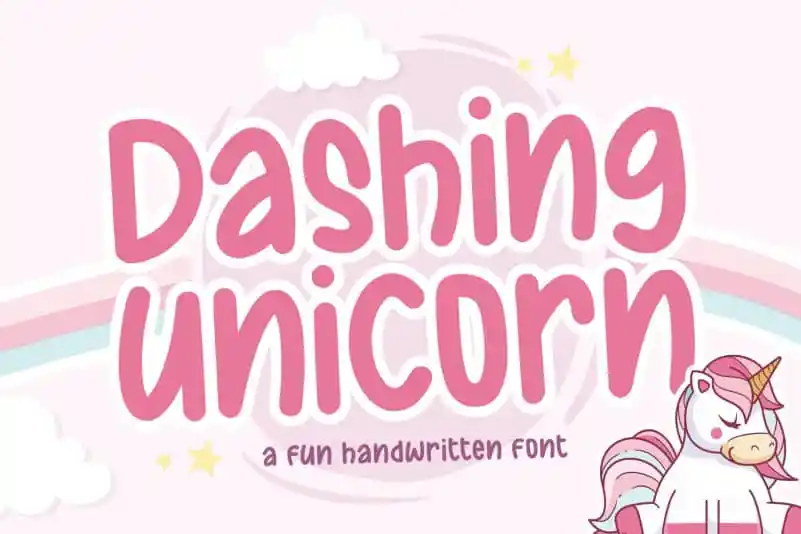
Dashing Unicorn Handwritten Font – Fonte Grátis
Dashing Unicorn Handwritten Font
A fonte Dashing Unicorn Handwritten é uma escolha perfeita para aqueles que desejam adicionar um toque único e criativo a seus projetos digitais. Seja para embalagens de produtos, criação de marca, revistas ou redes sociais, este script delicado consegue capturar o espírito do branding moderno com elegância. Para quem está planejando casamentos, essa fonte pode ser uma ótima maneira de destacar frases importantes em sua decoração nupcial. Essa fonte é especialmente indicada para criar um ar descontraído e único no seu design, sem comprometer a qualidade ou legibilidade da mensagem. E se você está buscando expressar palavras acima de um fundo em seus trabalhos digitais, esta escolha certamente atenderá suas necessidades. Com a fonte Dashing Unicorn Handwritten, designers gráficos e profissionais do marketing podem transformar seu trabalho digital em algo realmente único e memorável.